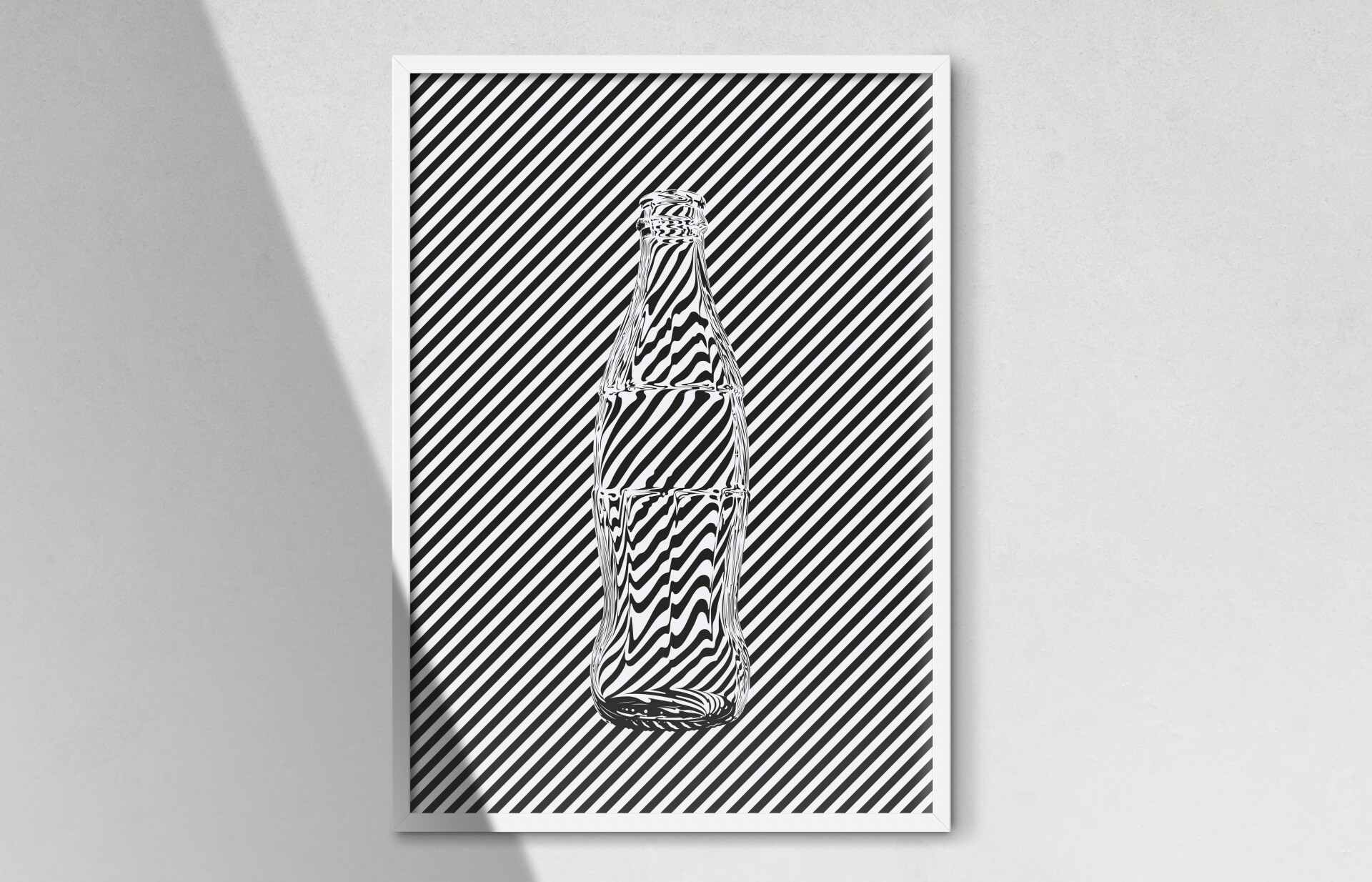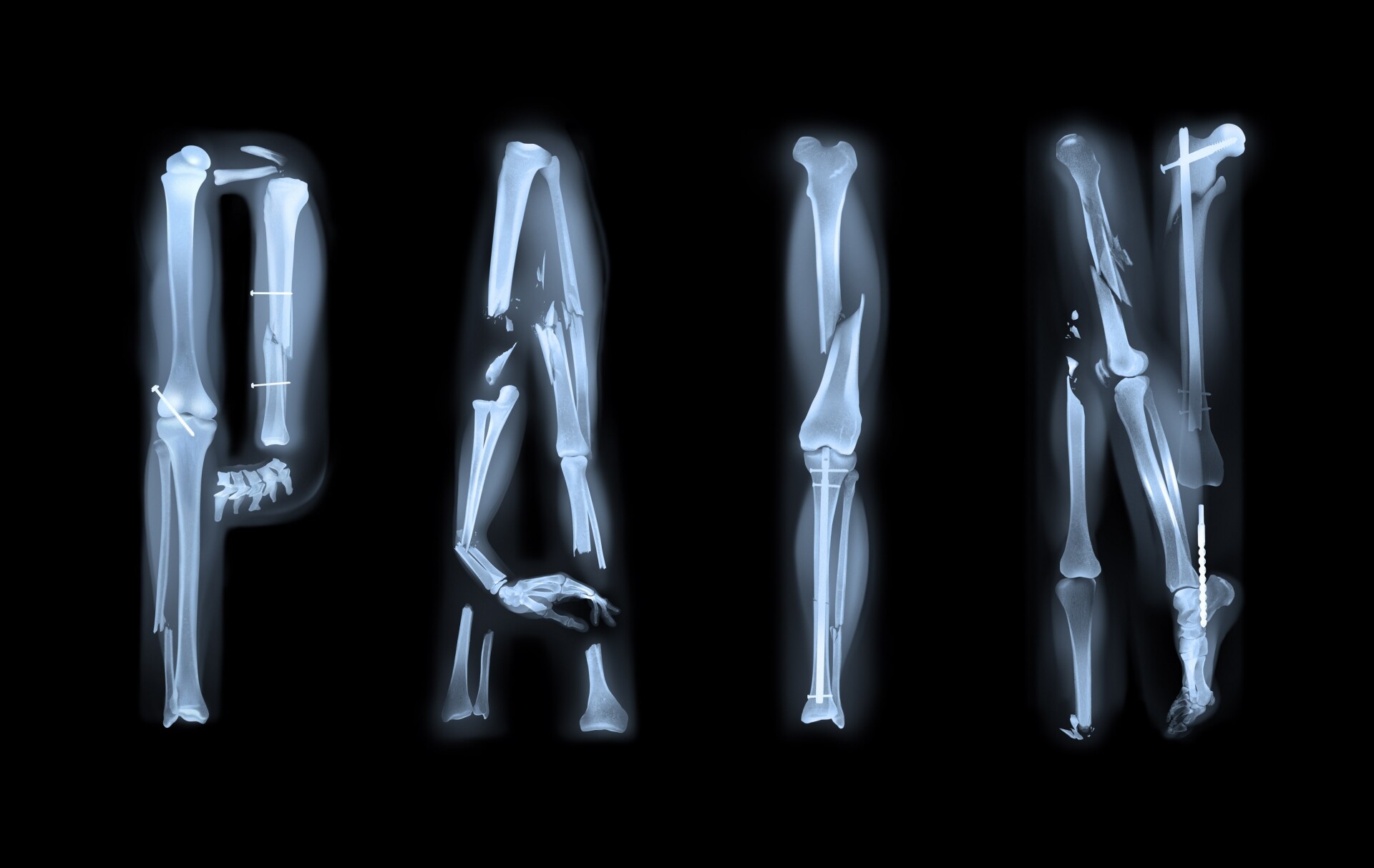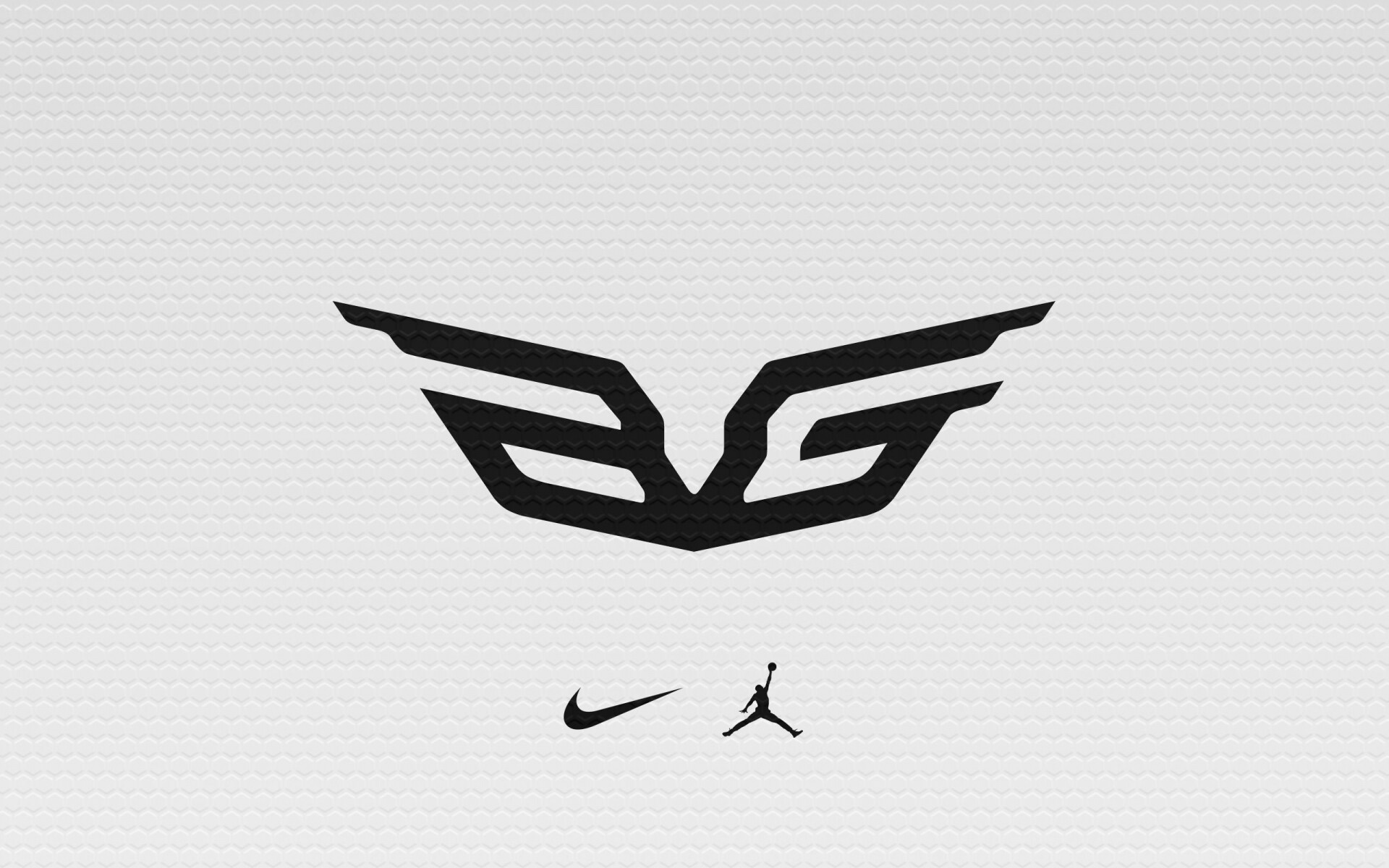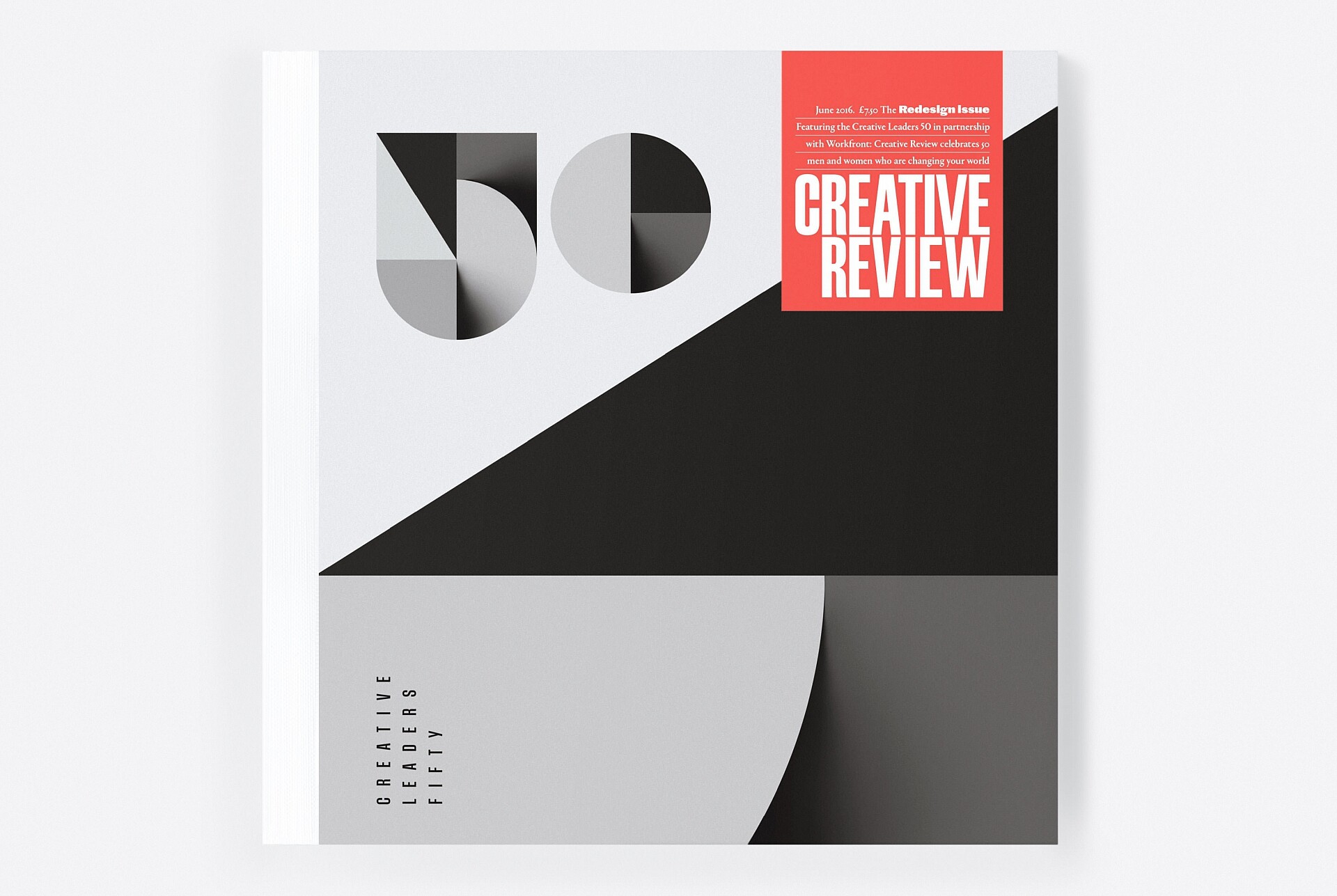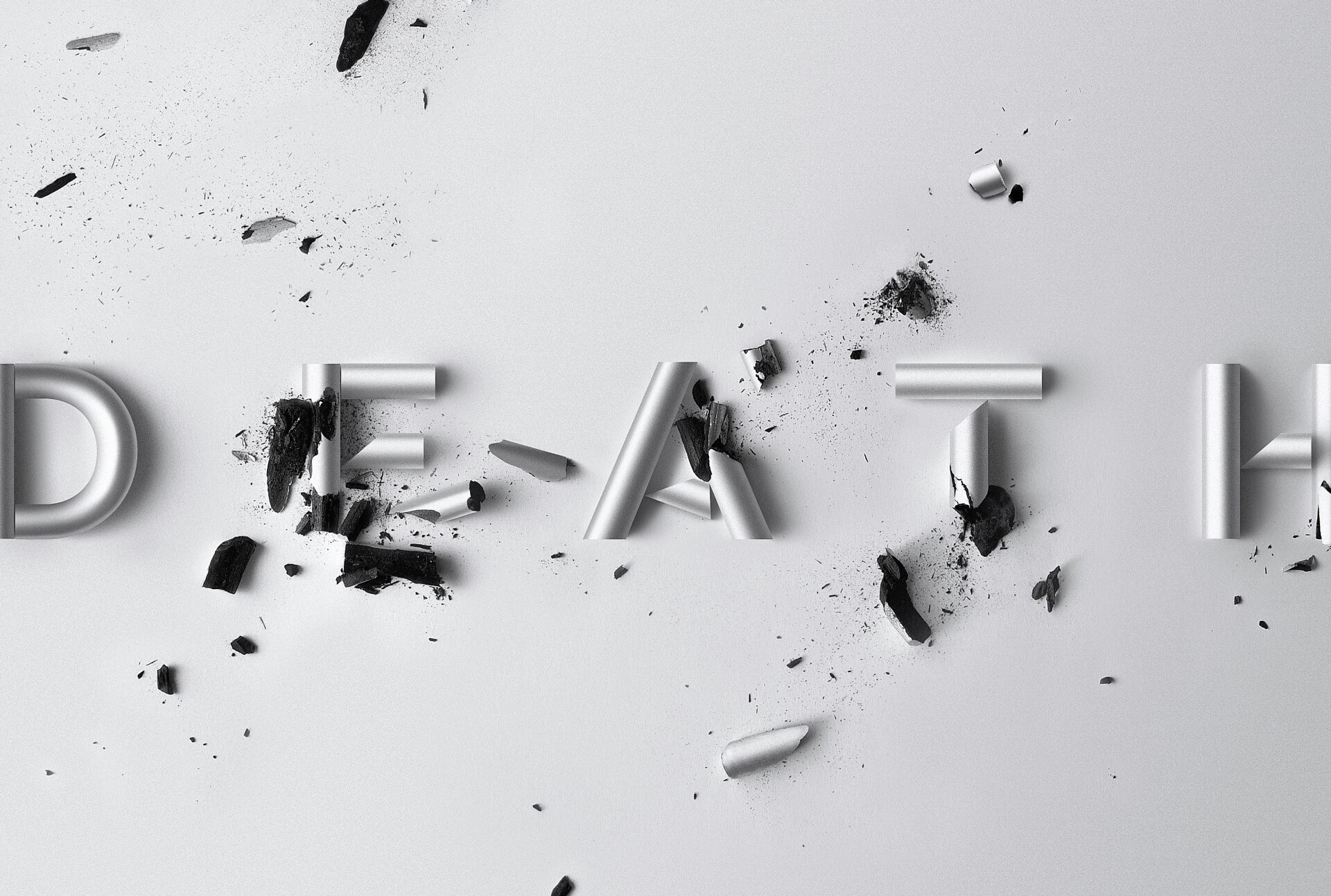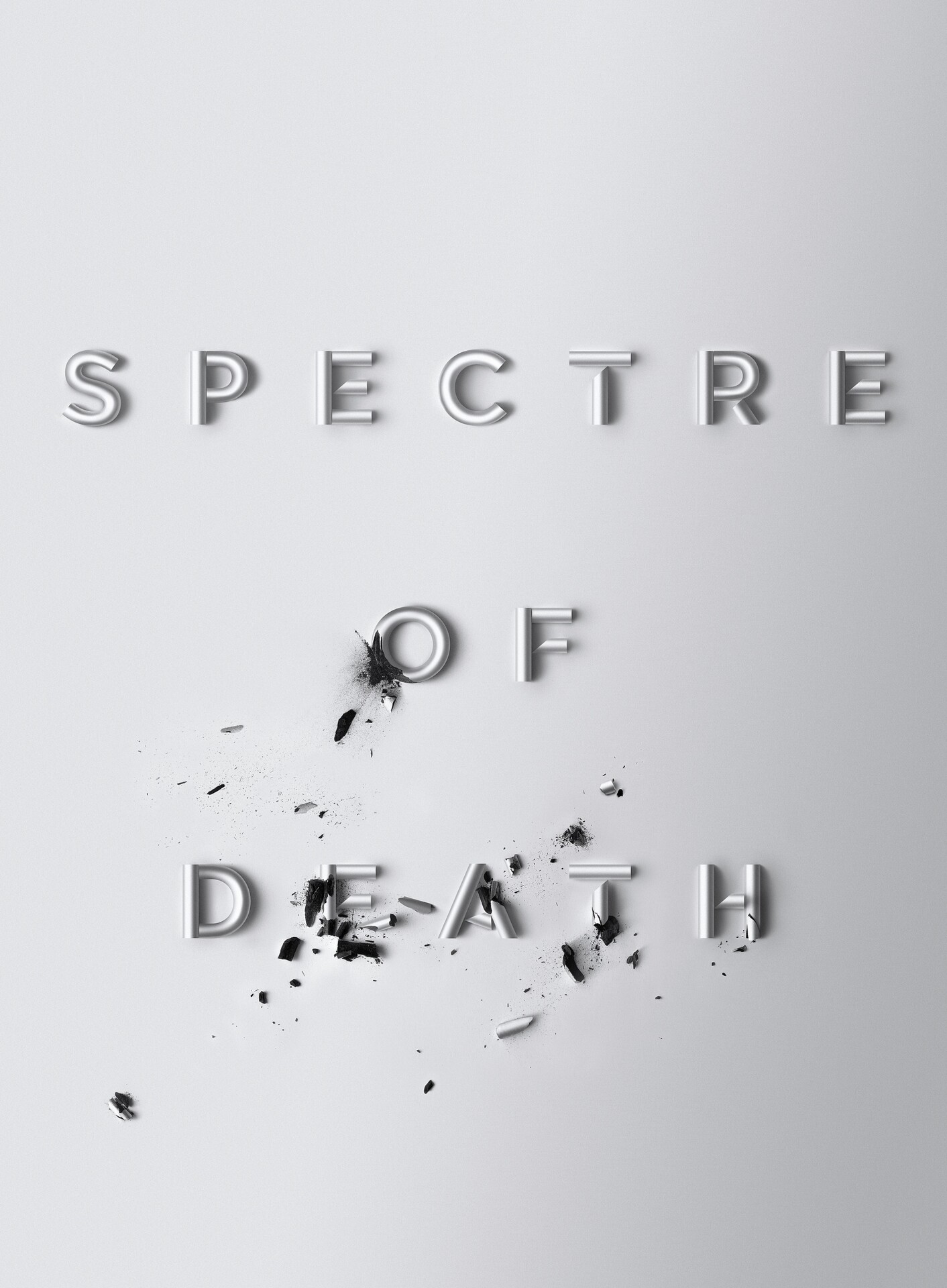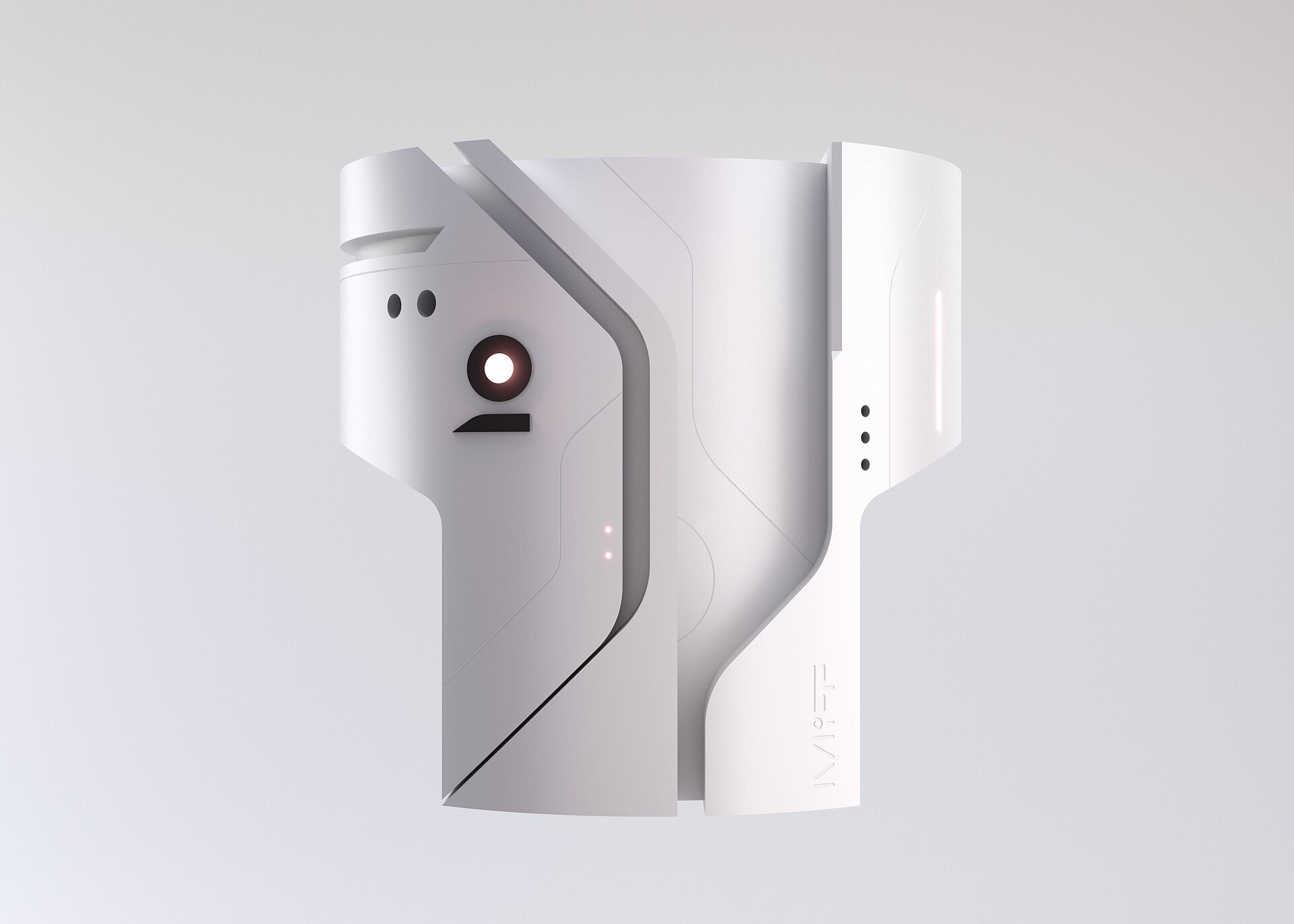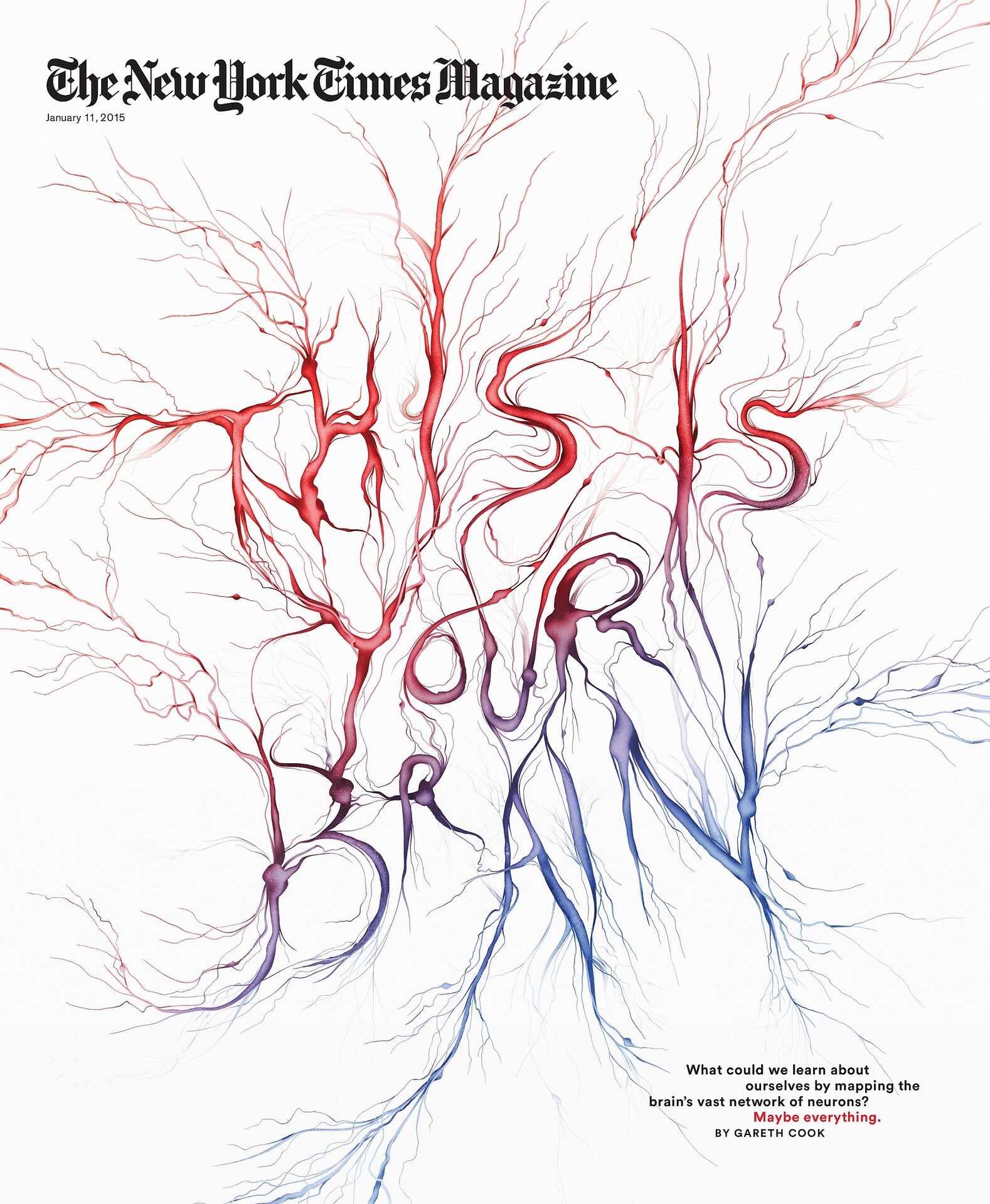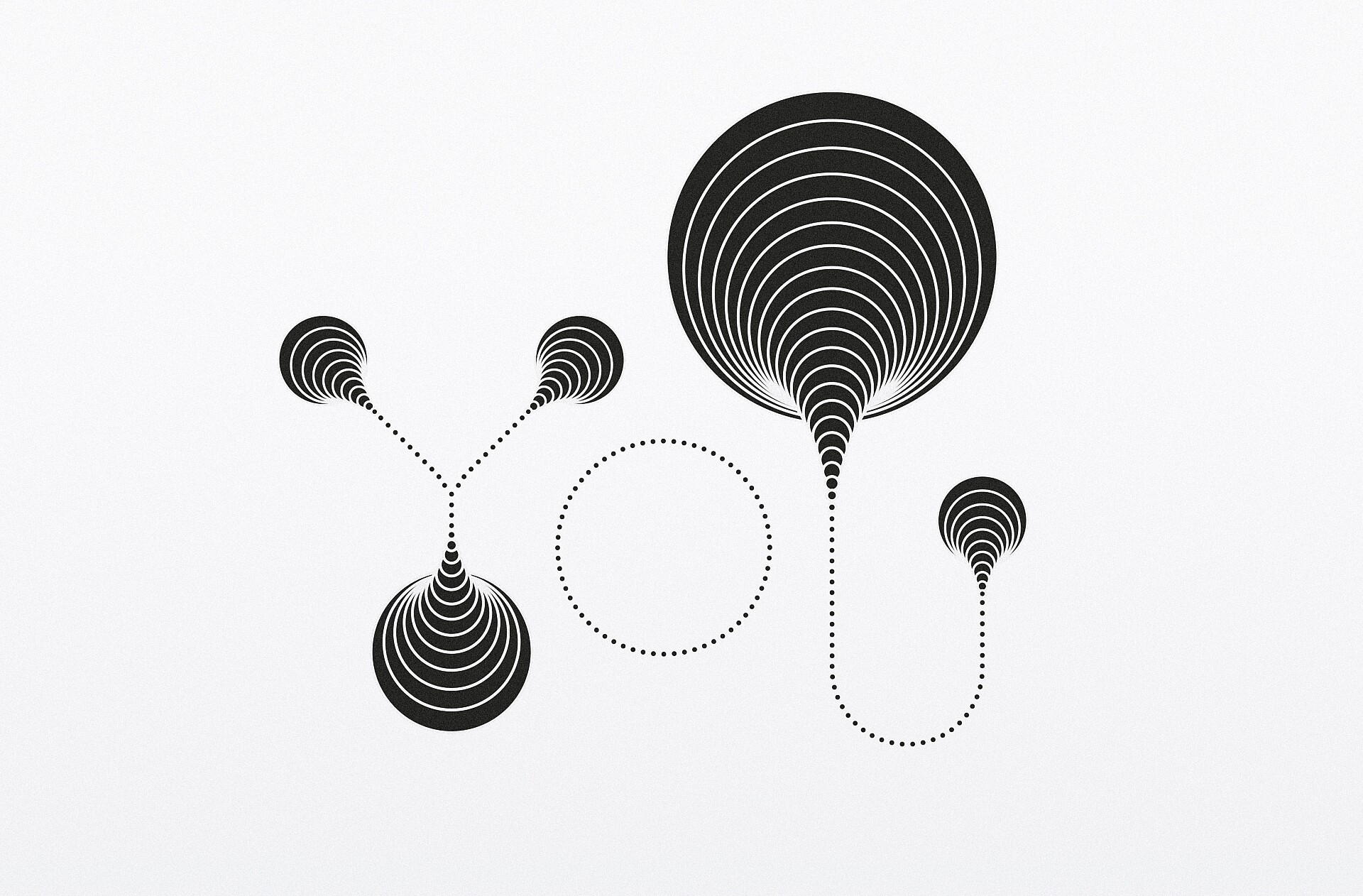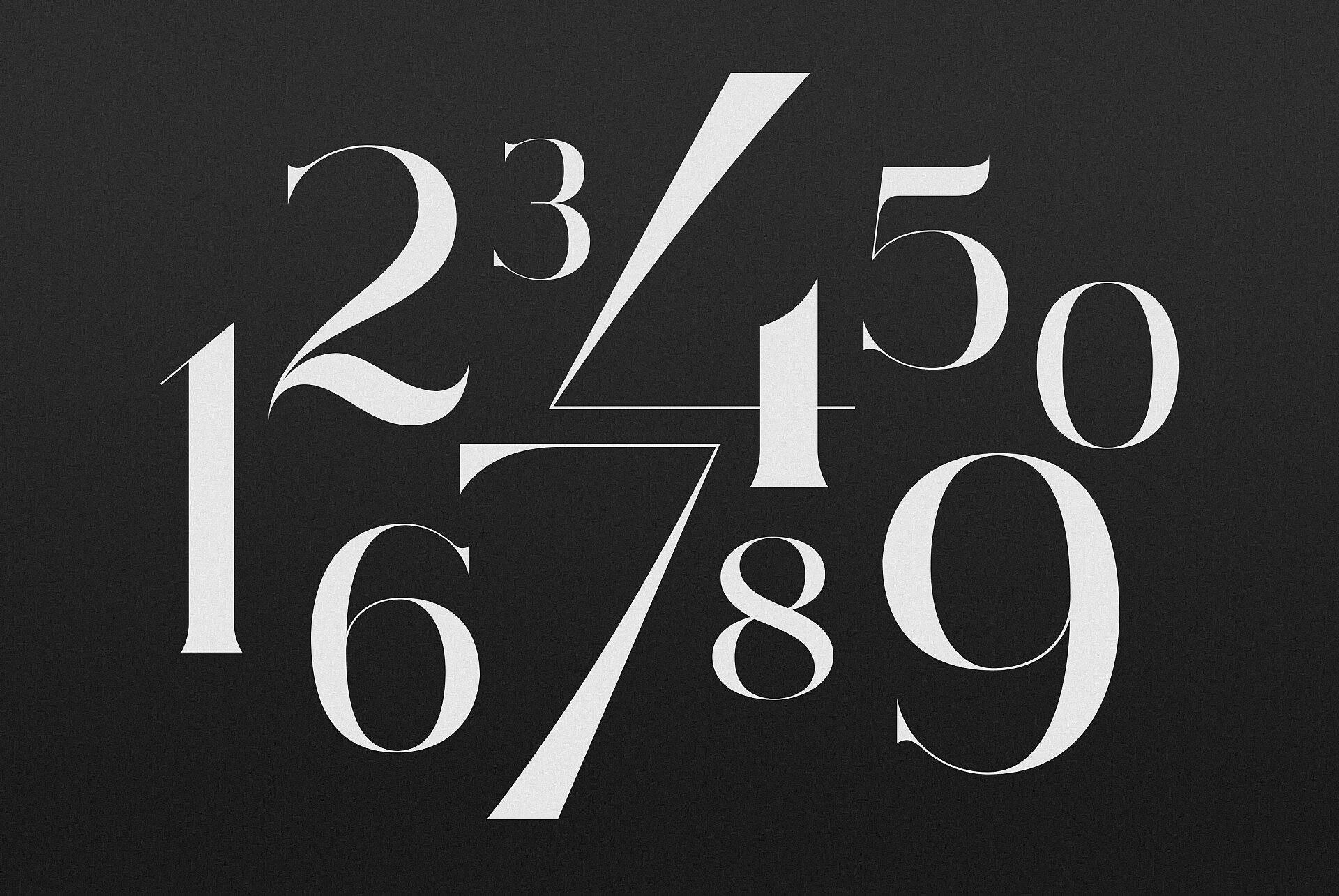
H φουτουριστική τυπογραφία των Sawdust
Πίσω από το όνομα Sawdust Studio κρύβεται η δημιουργική συνεργασία του Jonathan Quainton και του Rob Gonzalez. Τόσο στην επιφάνεια της οθόνης ενός υπολογιστή όσο και στο τυπωμένο χαρτί ενός περιοδικού, η αισθητική τους ακολουθεί μια ριζοσπαστική απομάκρυνση από την μαζική κουλτούρα, ακόμα και από τη θρυλική αποδόμηση της τυπογραφίας, όπως εξελίχθηκε στις αρχές της δεκαετίας του '90. Σήμερα, που τα στοιχεία της τυπογραφικής αποδόμησης έχουν ξεπεράσει την πραγματικότητα, και μετά τα «γράμματα» ήρθε η σειρά της εικόνας να αποδομηθεί μέσα από glitch ξυράφια που φτύνουν κατακερματισμένη διαφημιστική πληροφορία στους ανυποψίαστους πριν τα δελτία ειδήσεων, το μυαλό των Sawdust διαφωτίζει το μεταβαλλόμενο εσωτερικό τοπίο της ψηφιακής ζωής μας. Αντανακλά το συνεχώς αυξανόμενο ενδιαφέρον των υποψιασμένων, ταϊζοντάς το με θραύσματα μιας καλοστημένης σουίτας λογισμικού.
Ο ακραία ψυχρός ψηφιακός ρεαλισμός του έργου των Sawdust, μπορεί να μας βοηθήσει να κατανοήσουμε τι είναι ικανή να προσφέρει σήμερα η τεχνολογία στην τέχνη της τυπογραφίας.
Τυπογραφία για το περιοδικό IBM Systems Magazine, σε τεύχος σχετικό με τον προσδιορισμό της μετατόπισης από την επιλεκτική κρυπτογράφηση σε πλήρη διάχυτη κρυπτογράφηση.
Οι δύο βρετανοί σχεδιαστές συναντήθηκαν στο πανεπιστήμιο ενώ ετοίμαζαν την διπλωματική τους στο γραφιστικό σχέδιο. Έγιναν δύο καλοί φίλοι, αλλά στην πορεία εξελίχθηκαν και σε δύο πολύ καλούς συνεργάτες. Αποφάσισαν να συνεργαστούν γιατί και στους δύο αρέσουν τα έργα που προσφέρουν ένα βαθμό οπτικής εξερεύνησης, που μπορεί να είναι πιο απαιτητικά στην ανάγνωσή τους, που μπορεί να αναπαραχθούν από το σωρό των αχρησιμοποίητων ιδεών που έχουν στο μυαλό τους. Ο ακραία ψυχρός ψηφιακός ρεαλισμός του έργου τους, μπορεί να μας βοηθήσει να κατανοήσουμε τι μπορεί να προσφέρει σήμερα η τεχνολογία στην τέχνη της τυπογραφίας. Ολόκληρο το σύμπαν της ψηφιακής εποχής γίνεται ένα τοπίο στους χαρακτήρες που σχεδιάζουν: οι νέες ιδέες, οι φαντασιώσεις, η εκπληκτική τεχνολογική μεταρρύθμιση, η ικανότητα των μηχανών, η αναβαθμισμένη κλινική διαύγεια των σύγχρονων πίξελ, οι μύθοι της «δυστοπικής» κοινωνικής προόδου, η κομψότητα του κλασικού και της παραδοσιακής γραμμικής αφήγησης, το ανακάτεμα των γραμμάτων και των αριθμών σε ένα κείμενο που όλοι έχουμε μάθει να διαβάζουμε με ταχύτητα και ευκολία, χάρη στην ευρεία χρήση του διαδικτύου.
Τα έργα των Sawdust έχουν στολίσει μια τεράστια γκάμα περιοδικών και εφημερίδων: από το τεχνολογικό Wired (σε όλες τις πιθανές εκδόσεις που κυκλοφορεί από Αμερική μέχρι Ιταλία) μέχρι το θρυλικό Εsquire και τους New York Times. Ανάμεσα στους πελάτες του Sawdust Studio θα βρει κανείς κολοσσούς όπως την Coca-Cola, την ΙΒΜ, την Nike, την Audi, την Honda, την Converse ή την Dolby. Κι ενώ η ιδιορρυθμία της τυπογραφίας τους δεν φαίνεται να δίνει δεκάρα για τη διάκριση ανάμεσα στο φανερό και το κρυφό περιεχόμενο της πραγματικότητας που καλούνται να υπηρετήσουν, το καλλιτεχνικό δίδυμο έχει εδώ και καιρό αφήσει πίσω του τον διάδρομο επιτάχυνσης, έχει κυριολεκτικά "ξεφύγει" και πλέον βρίσκεται σε τροχιά για την ολοκλήρωση της τυπογραφικής του φιλοσοφίας.
Αφίσα για τα 100 χρόνια του εμβληματικού μπουκαλιού της Coca-Cola στην έκθεση «Τhe Coca-Cola Bottle: An American Icon at 100» στο High Museum of Art της Ατλάντα.
Τυπογραφικό έργο για το εξώφυλλο του περιοδικού της Audi.
Tυπογραφία για ένα άρθρο του αμερικανικού Wired αφιερωμένο στους νέους χάκερ που προορίζονται να κυριαρχήσουν στον κόσμο της τεχνολογίας.
Εξώφυλλο για τους New York Times βασισμένο στο κεντρικό θέμα που καταγράφει την ιστορία του καθηγητή Sebastien Seung από το Πανεπιστήμιο του Πρίνστον και την προσπάθειά του να χαρτογραφήσει τις νευρικές οδούς του εγκεφάλου.
Γραμματοσειρά ειδικά σχεδιασμένη για το βρετανικό Wired.
Εξώφυλλο για το βρετανικό περιοδικό Creative Review.
Γραμματοσειρά ειδικά σχεδιασμένη για το ιταλικό Wired.
Άνοιγμα για άρθρο του περιοδικού Entertainment Weekly αφιερωμένο στην ταινία του Τζέιμς Μποντ "Spectre".
Τυπογραφία κατά παραγγελία για άρθρο του περιοδικού Men's Health για τον πόνο.
Σχέδιο για το εξώφυλλο του περιοδικού ΜΙΤ Technology Review, ειδικά σχεδιασμένο για το τεύχος "Best in Tecn 2017"
Τυπογραφικό σχέδιο για το ετήσιο τεύχος του Wired Design Issue με θέμα την αρχιτεκτονική.
Τα νούμερα της γραμματοσειράς Quainton που μπορεί να αγοράσει κανείς από το Hype for Type.
Τυπογραφικό σχέδιο για το βιβλίο OFFF "Archetype".
Σχεδιασμός λογοτύπου και μάρκας για τον αμερικανό παίκτη του NBA Blake Griffin για λογαριασμό της Nike.